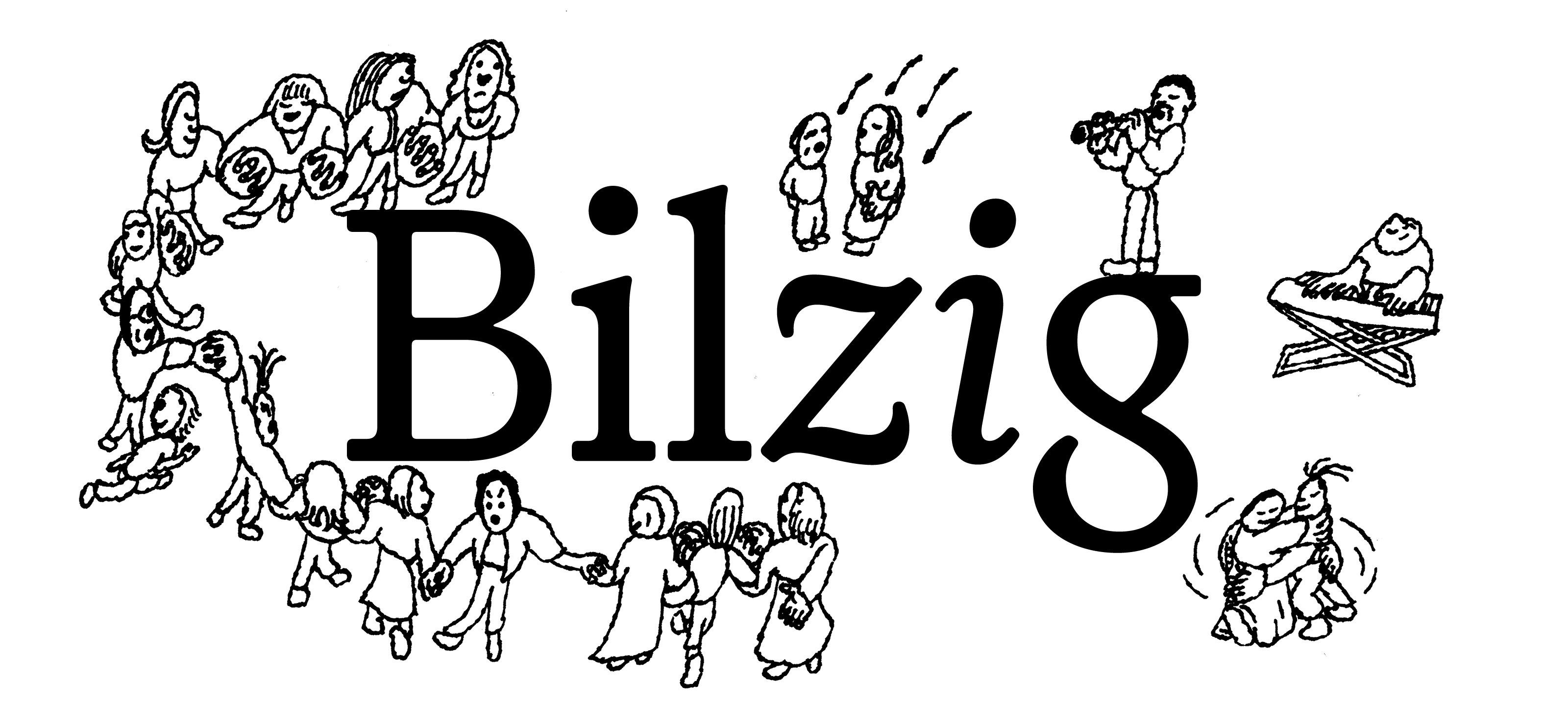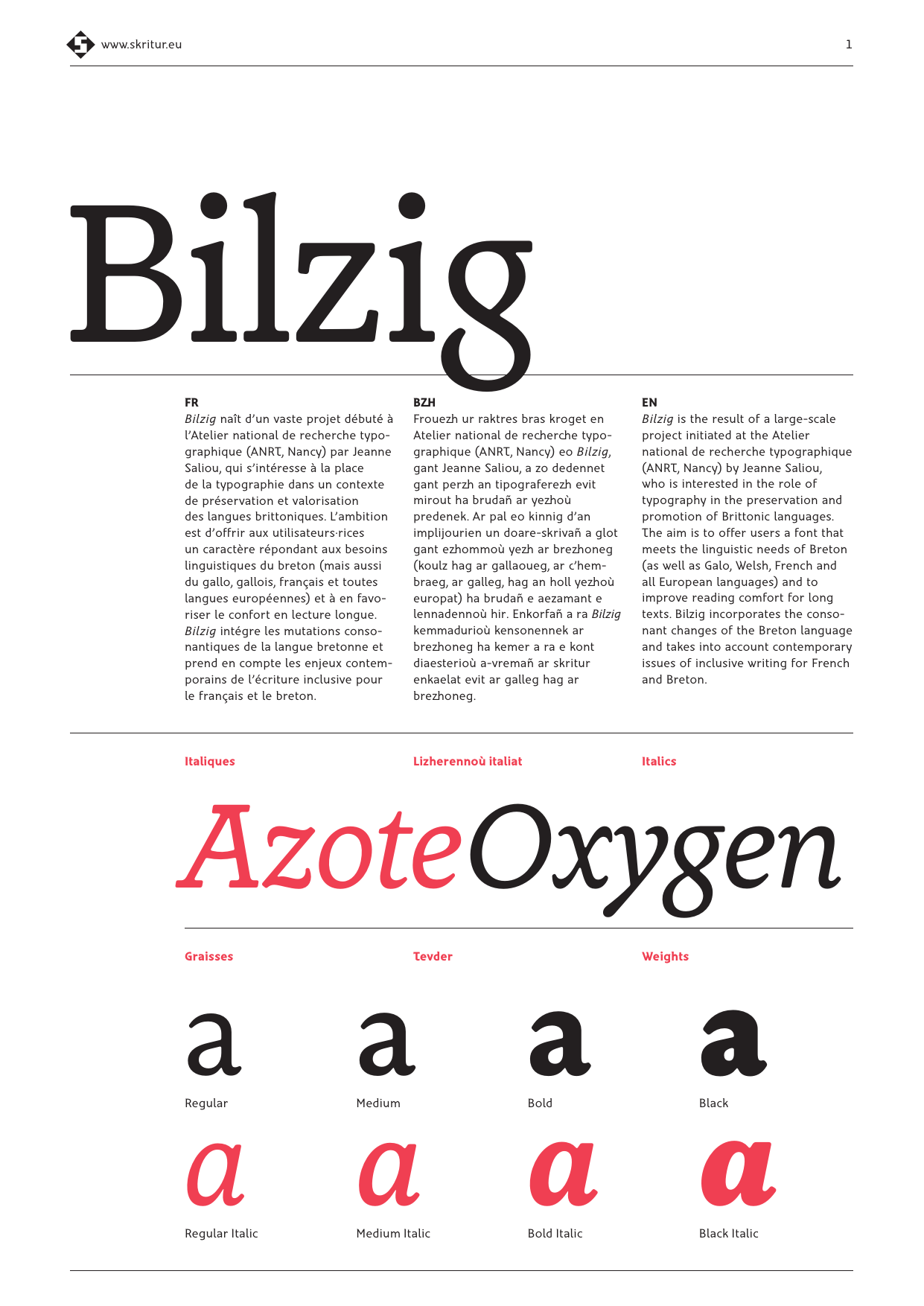
Bilzig Collection
Bilzig
Bilzig naît d’un projet de recherche de Jeanne Saliou qui s’intéresse à la place de la typographie dans un contexte de préservation et valorisation des langues brittoniques. L’ambition est d’offrir aux utilisateurs·rices un caractère répondant aux besoins linguistiques du breton (mais aussi du gallo, gallois, français et toutes langues européennes) et à en favoriser le confort en lecture longue. Bilzig intégre les mutations consonantiques de la langue bretonne et prend en compte les enjeux contemporains de l’écriture inclusive pour le français et le breton. Vive le Bilzig!
Conception typogaphique: Jeanne Saliou
Developpement & production typographique: Malou Verlomme
Design et communication: Yoann De Roeck
Bilzig
Ganet eo bet Bilzig diwar raktres enklask Jeanne Saliou dedennet ma’z eo-hi gant perzh an tipografiezh e-keñver gwareziñ ha brudañ ar yezhoù predenek. Ar pal eo kinnig d’an implijourien un doare-skrivañ a glot gant ezhommoù yezhel ar brezhoneg (koulz hag ar gallaoueg, ar c’hembraeg, ar galleg, hag an holl yezhoù europat) ha brudañ e aezamant e lennadennoù hir. Enkorfañ a ra Bilzig kemmadurioù kensonennek ar brezhoneg ha kemer a ra e kont diaesterioù a-vremañ ar skritur enkaelat evit ar galleg hag ar brezhoneg. Bevet Bilzig !
Tresadenn tipografek: Jeanne Saliou
Diorren ha produiñ tipografek : Malou Verlomme
Skeudennoù ha kehentiñ : Yoann De Roeck
Bilzig
Bilzig was born out of a research project by Jeanne Saliou focusing on the role of typography in the preservation and promotion of Brittonic languages. The aim is to offer users a font that meets the linguistic needs of Breton (as well as Galo, Welsh, French and all European languages) and to improve reading comfort for long texts. Bilzig incorporates the consonant changes of the Breton language and takes into account contemporary issues of inclusive writing for French and Breton. Vive le Bilzig !
Typeface design: Jeanne Saliou
Typeface Development & production: Malou Verlomme
Graphic design & communication: Yoann De Roeck